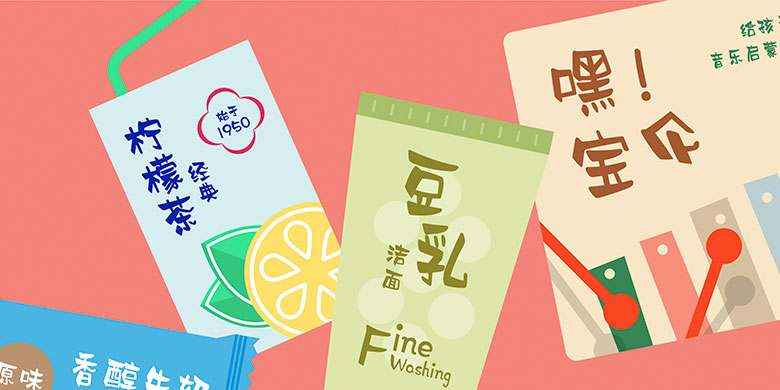
方正马克体 简 方正马克体是一款融合了手绘POP的创意字体。书写果断,充满活力,意趣十足。整体风格新颖可爱,特色鲜明。适用于餐饮类产品包装设计,商业类趣味广告和新媒体宣传设计。 方正马克体 品牌: 方正字库 设计师: 何德林 发行时间:2019 字库编码:大陆简体(GB2312-80) 分类:创意字体 字体下载 官网下载